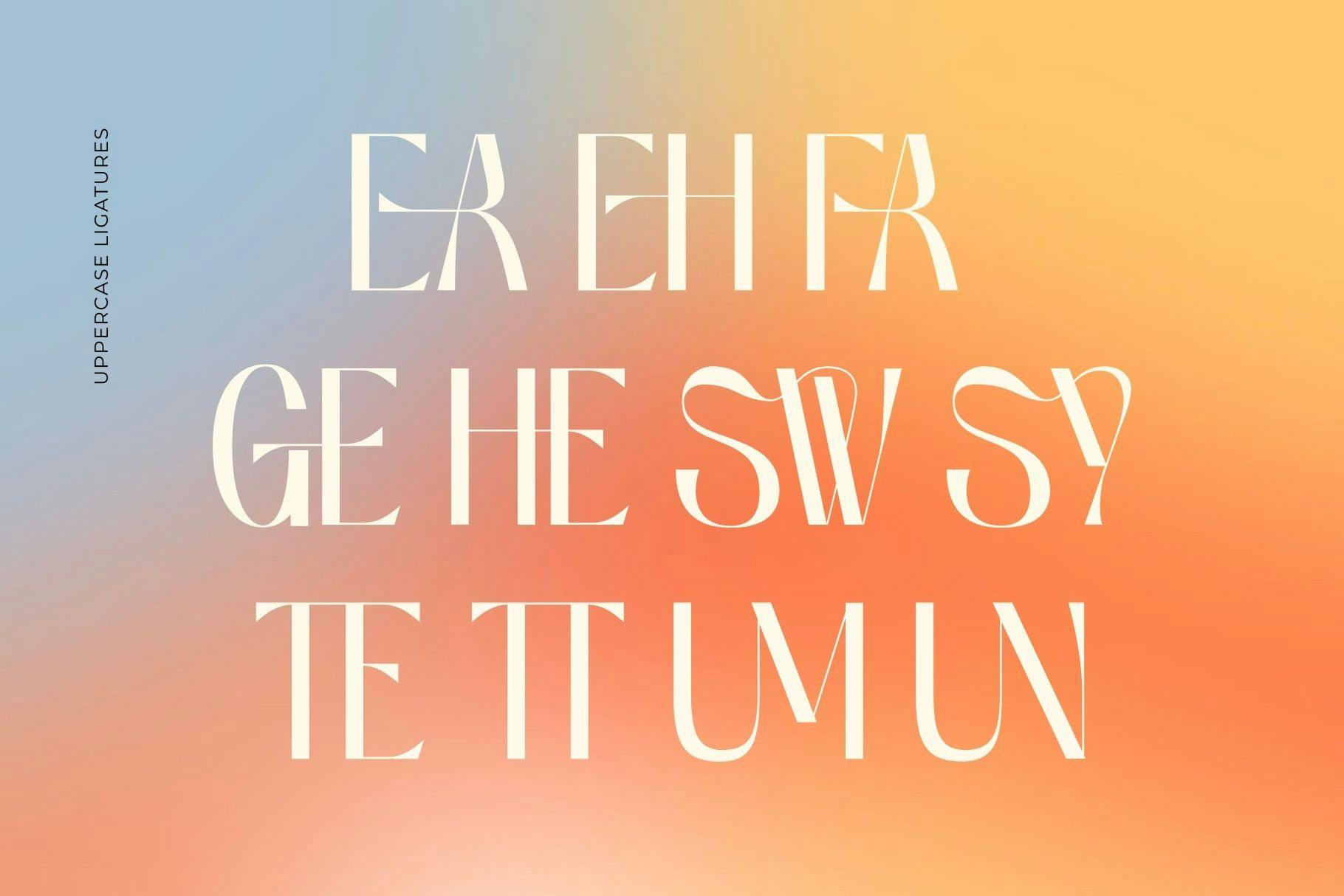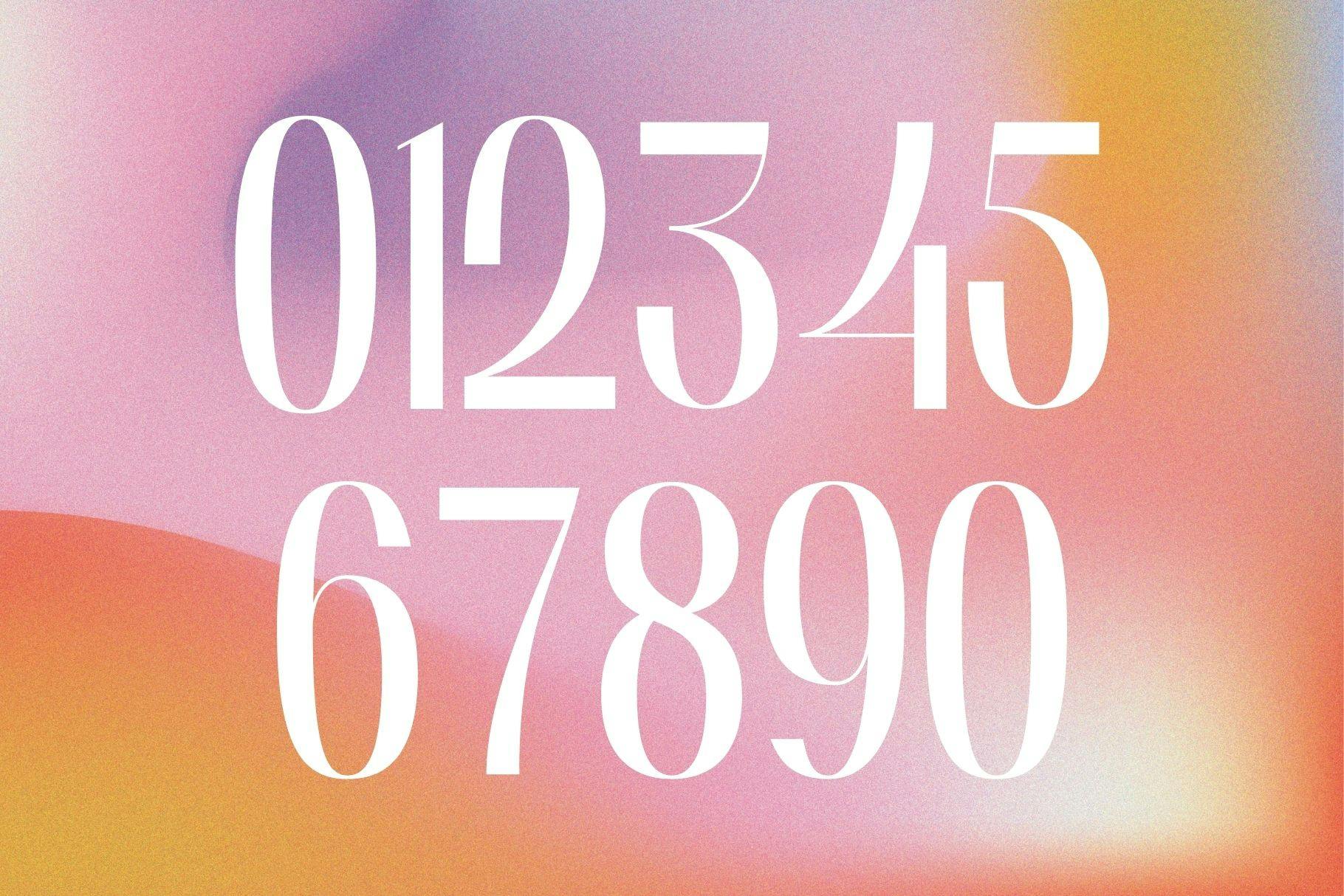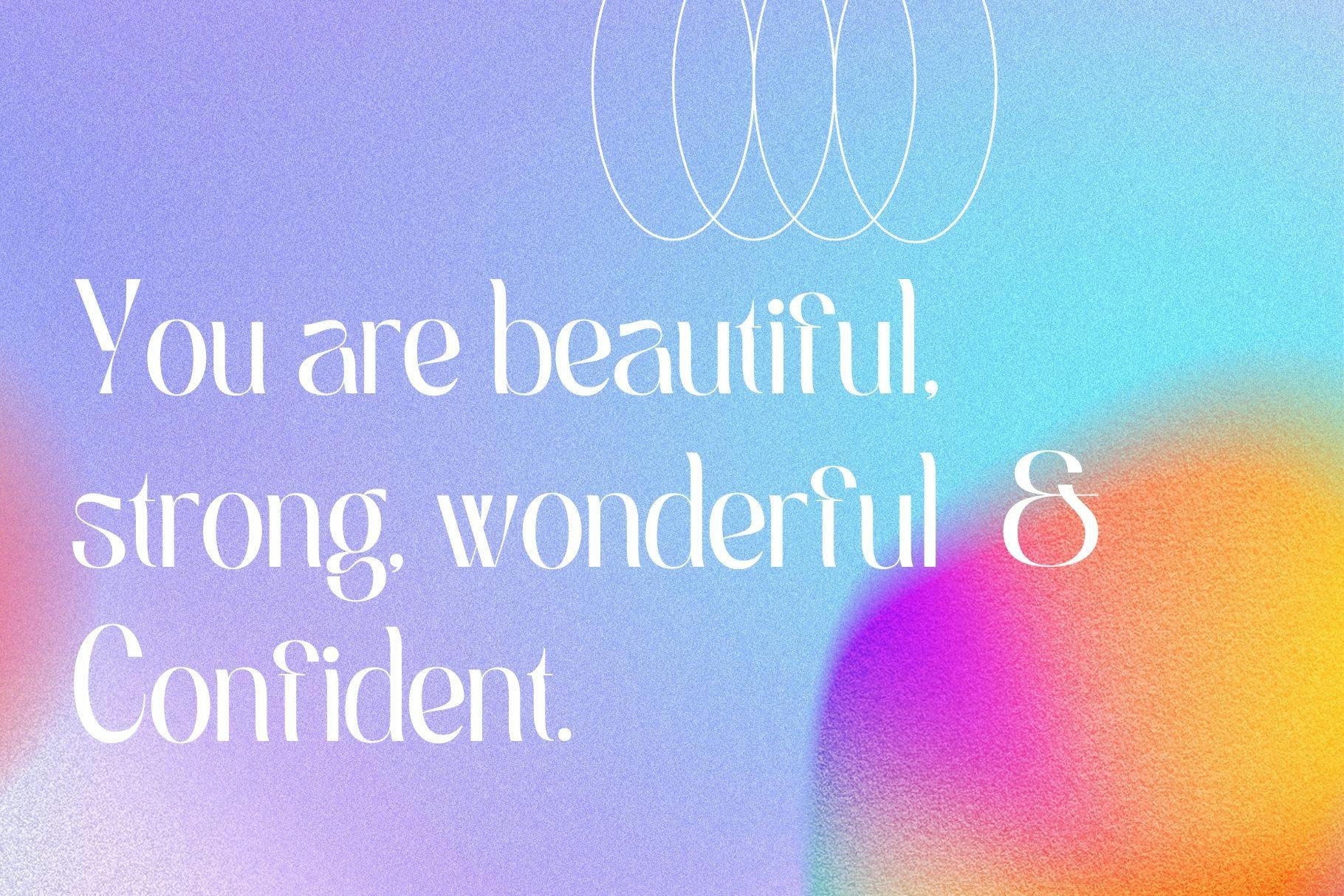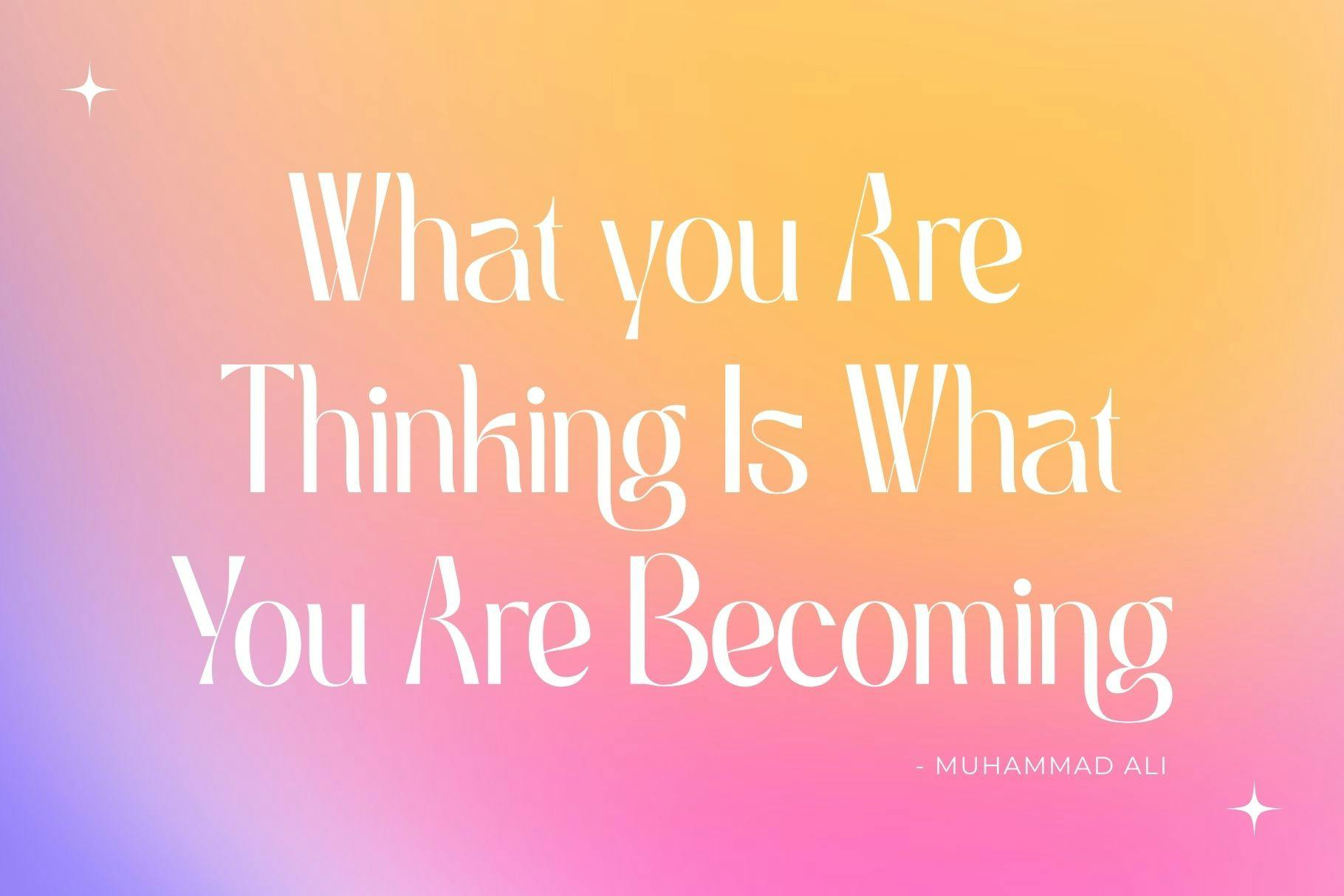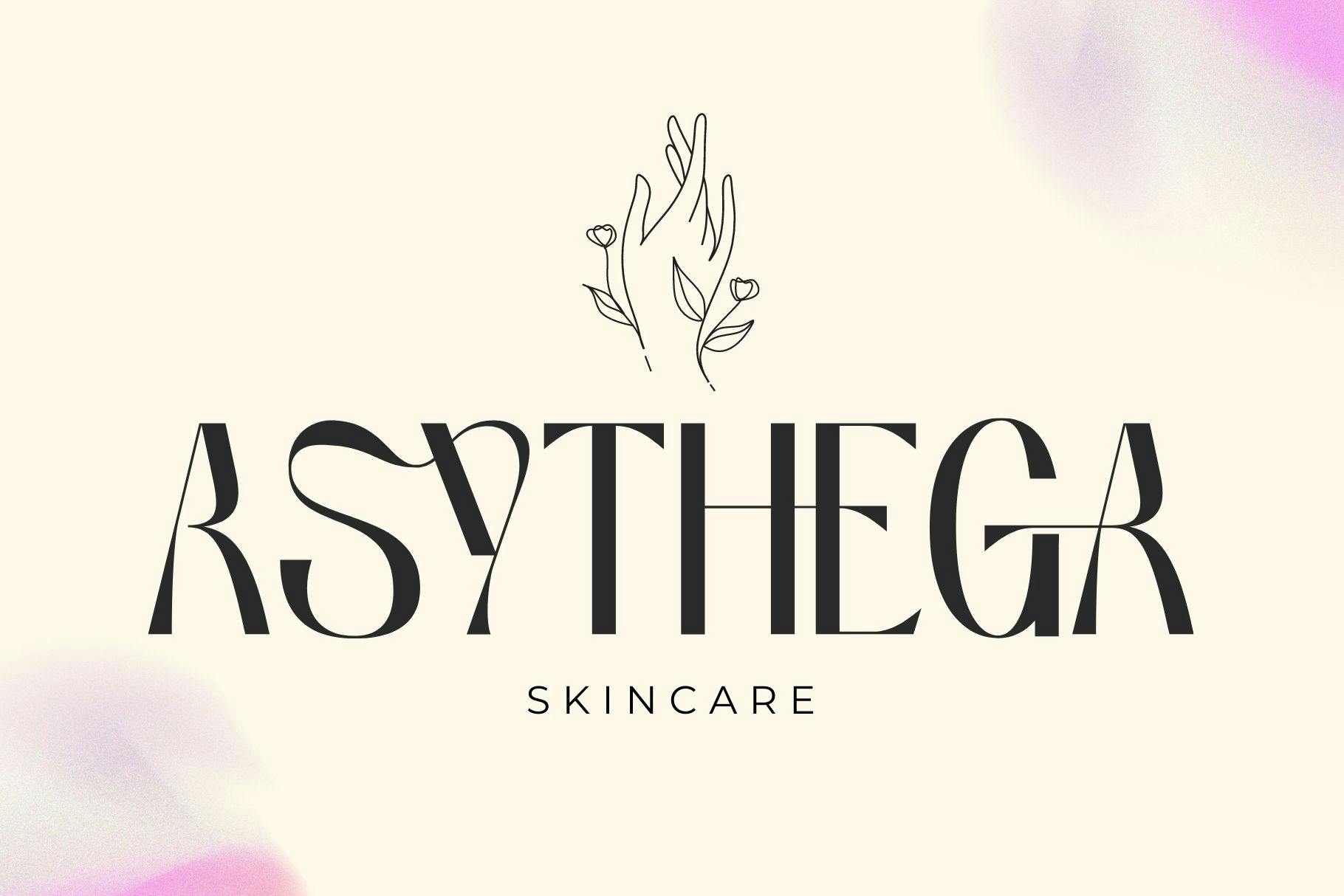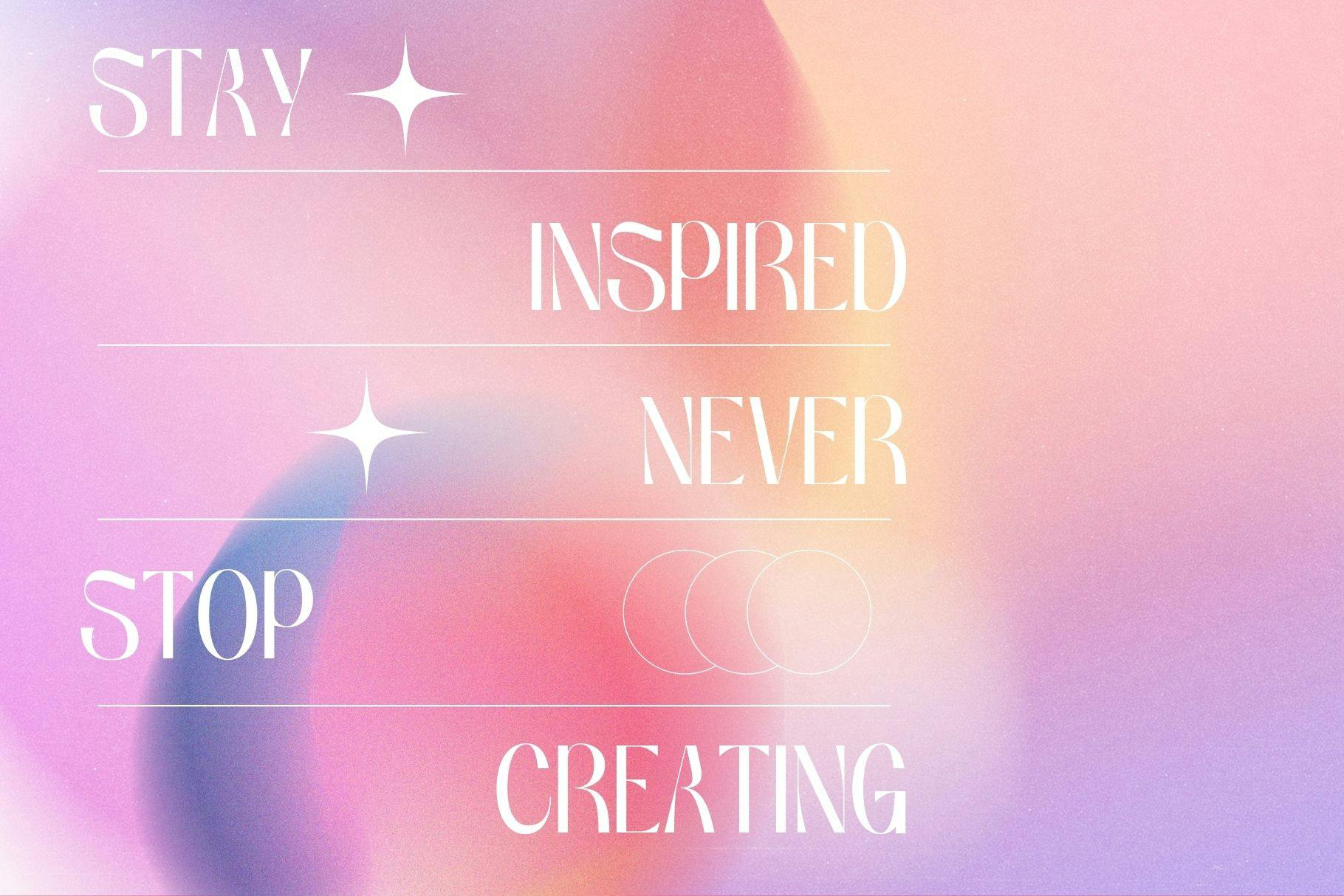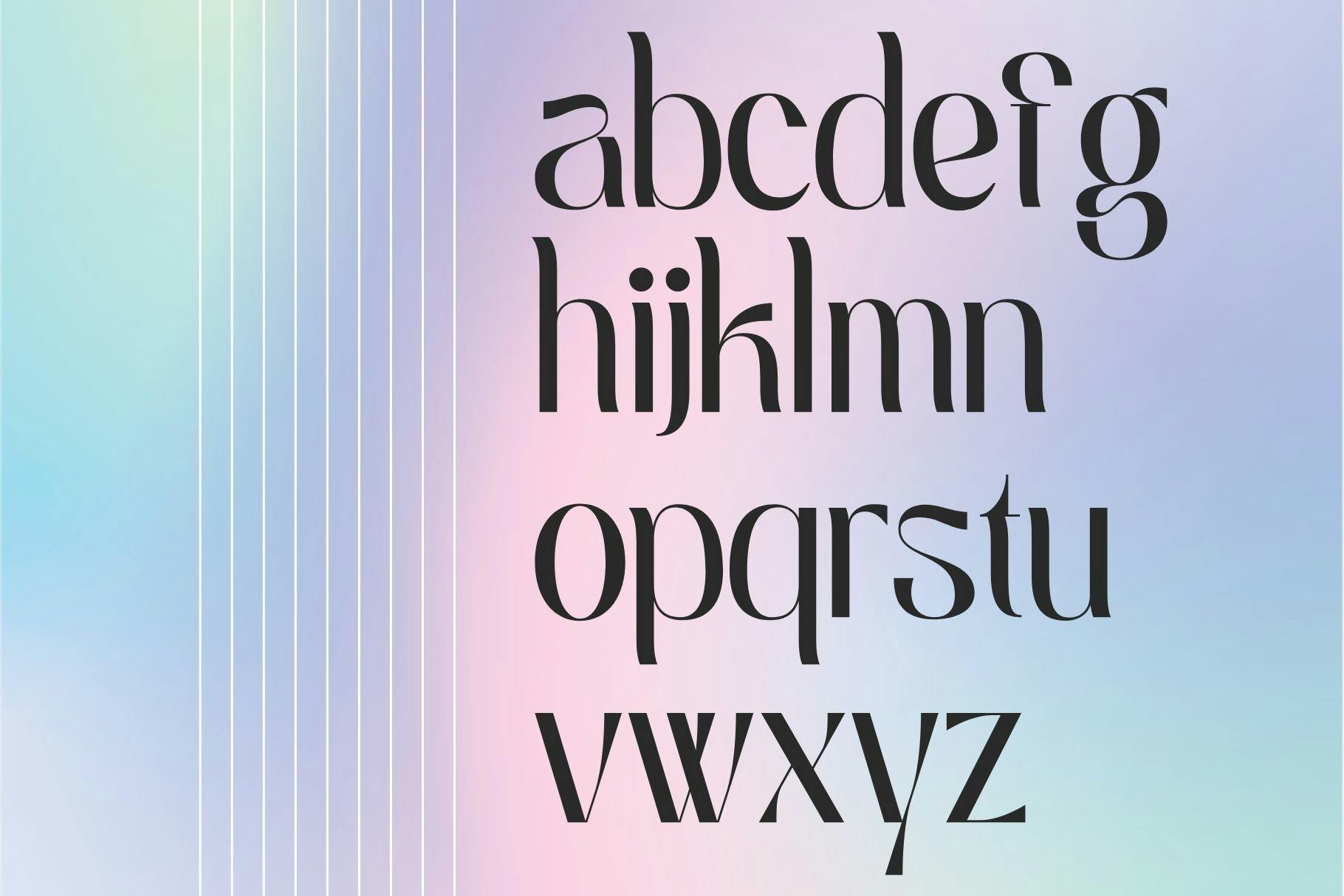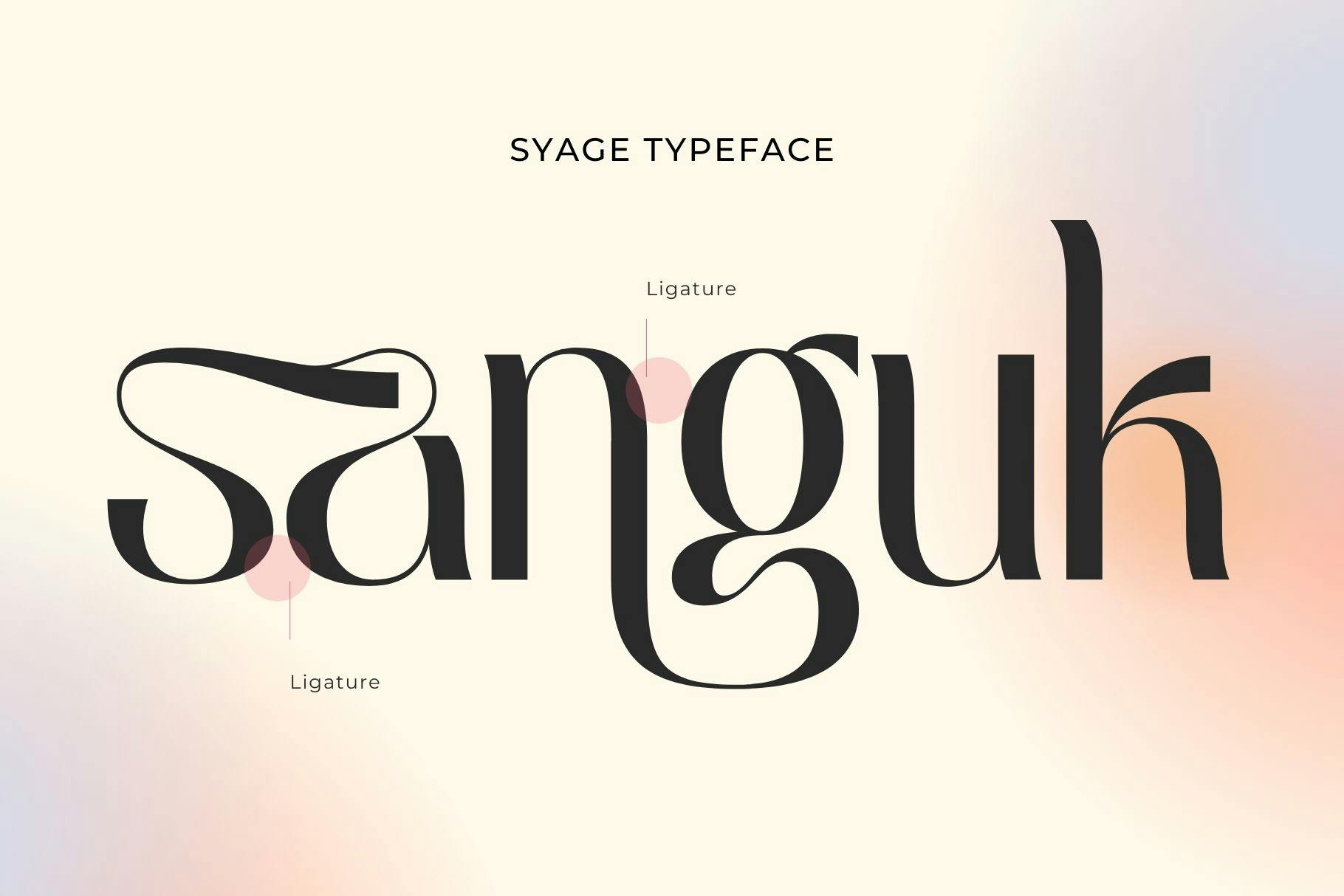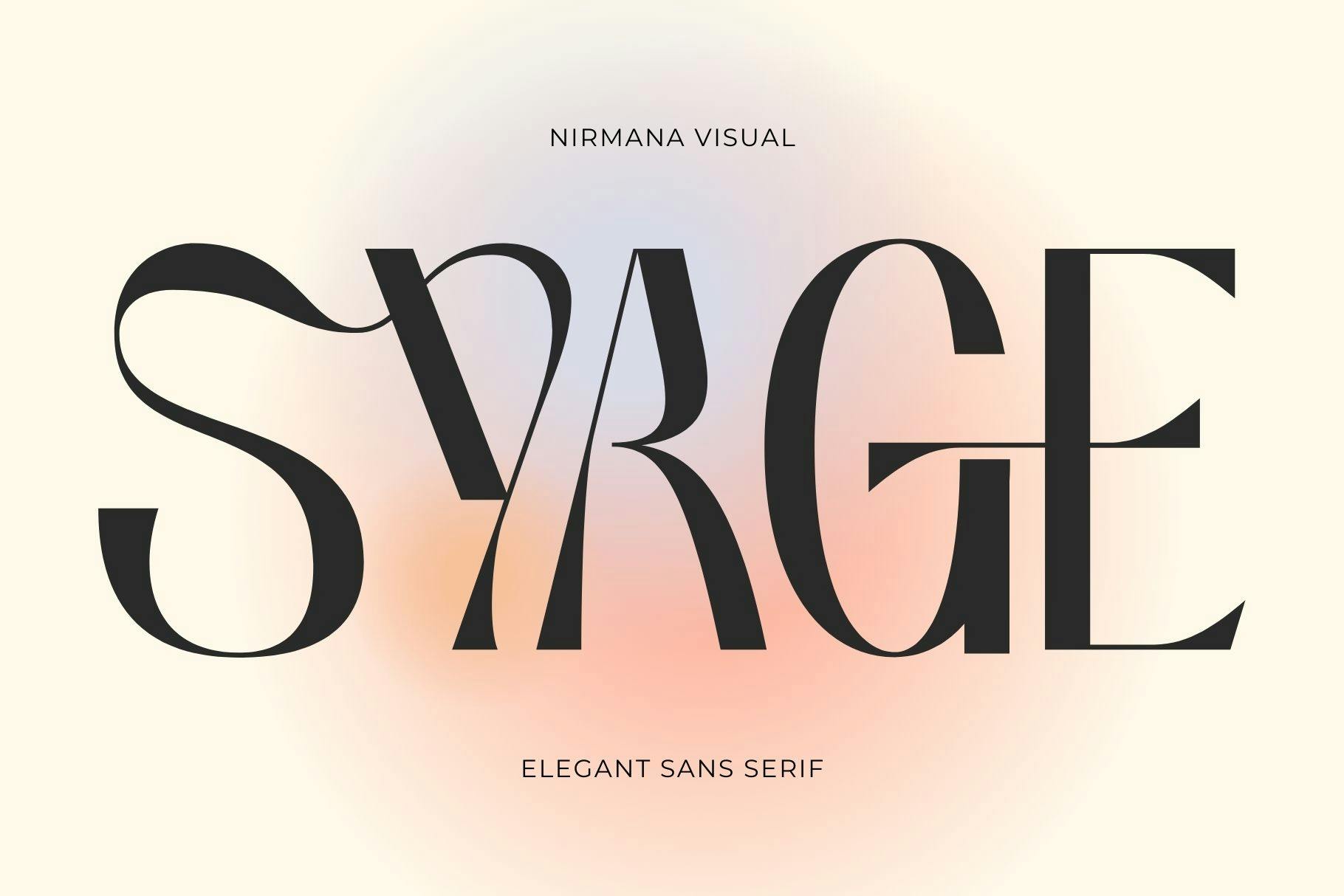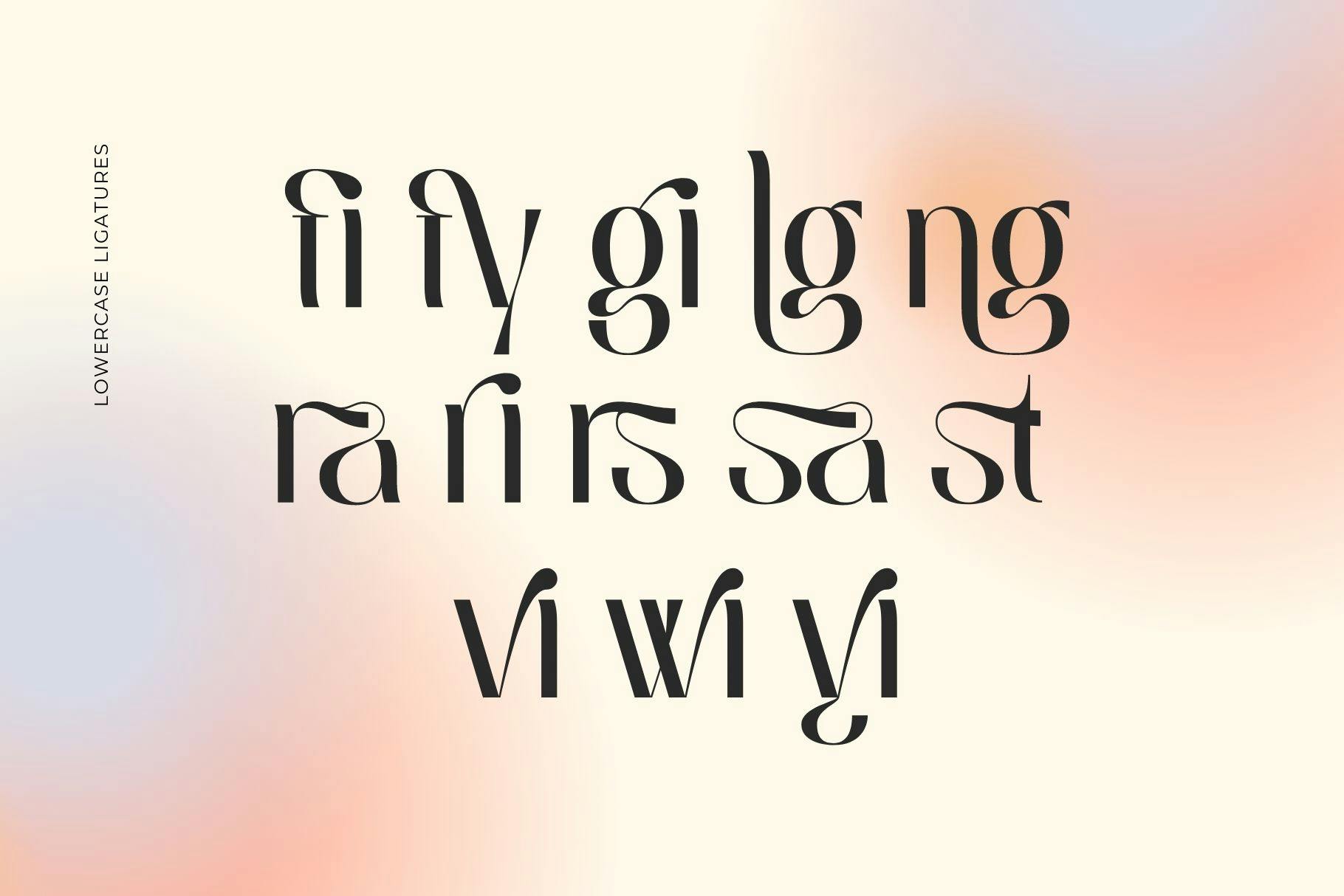
Syage یک فونت معاصر از نوع Sans Serif است.
این فونت هارمونی زیبای تایپوگرافی را برای پروژههای طراحی متنوع از جمله لوگو و برندسازی، پستهای رسانههای اجتماعی، تبلیغات و طراحی محصولات ارائه میدهد.